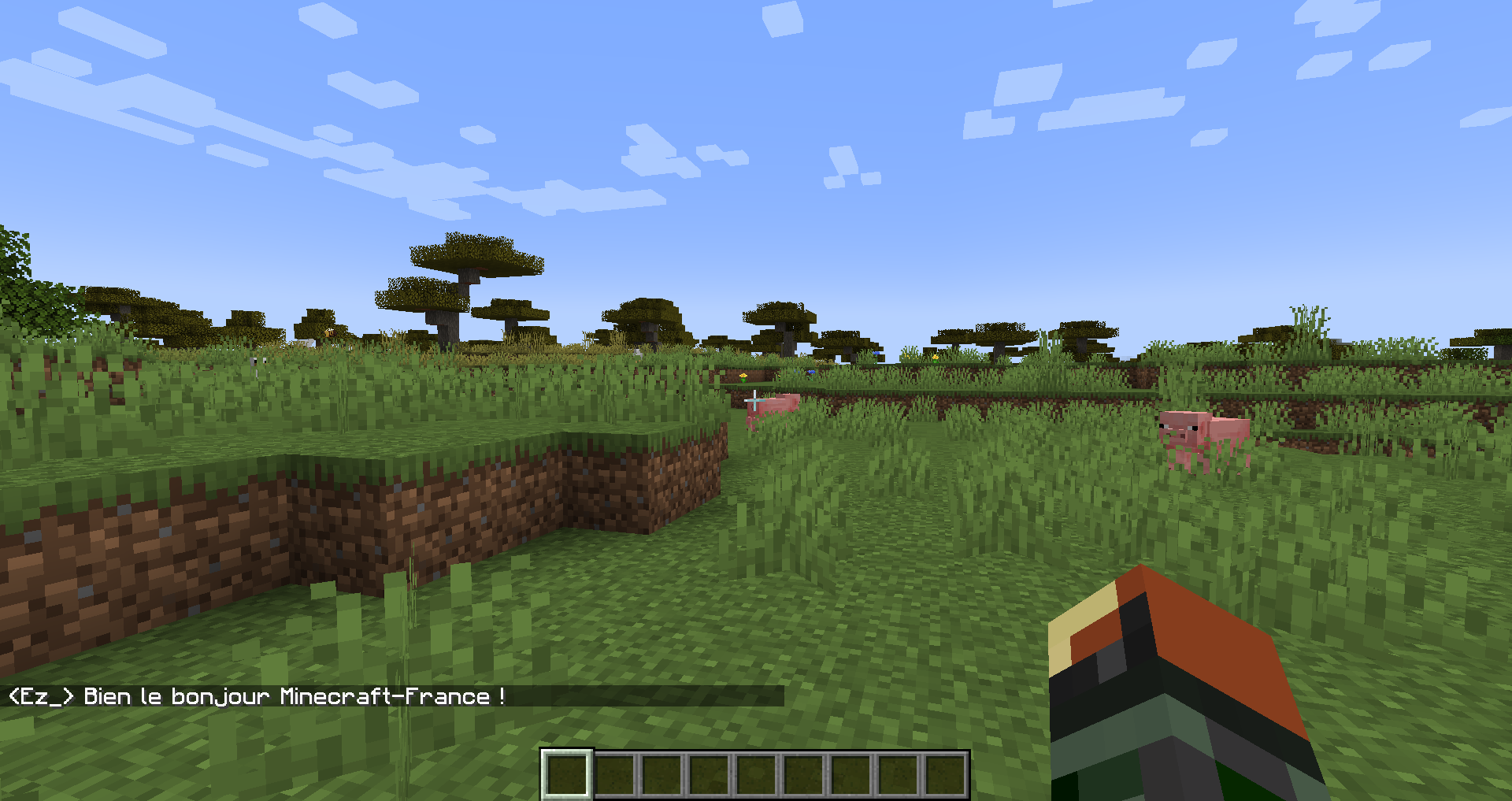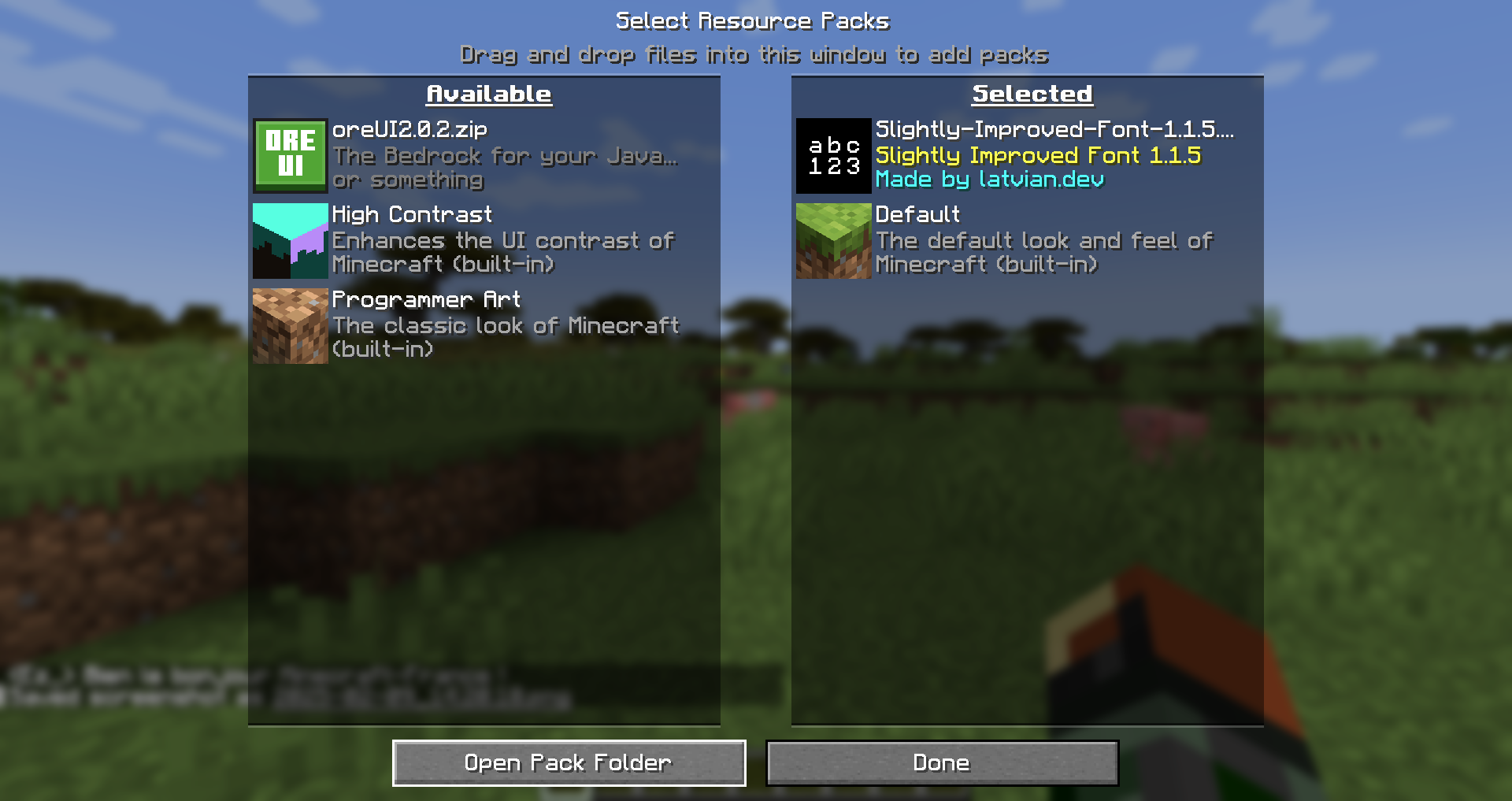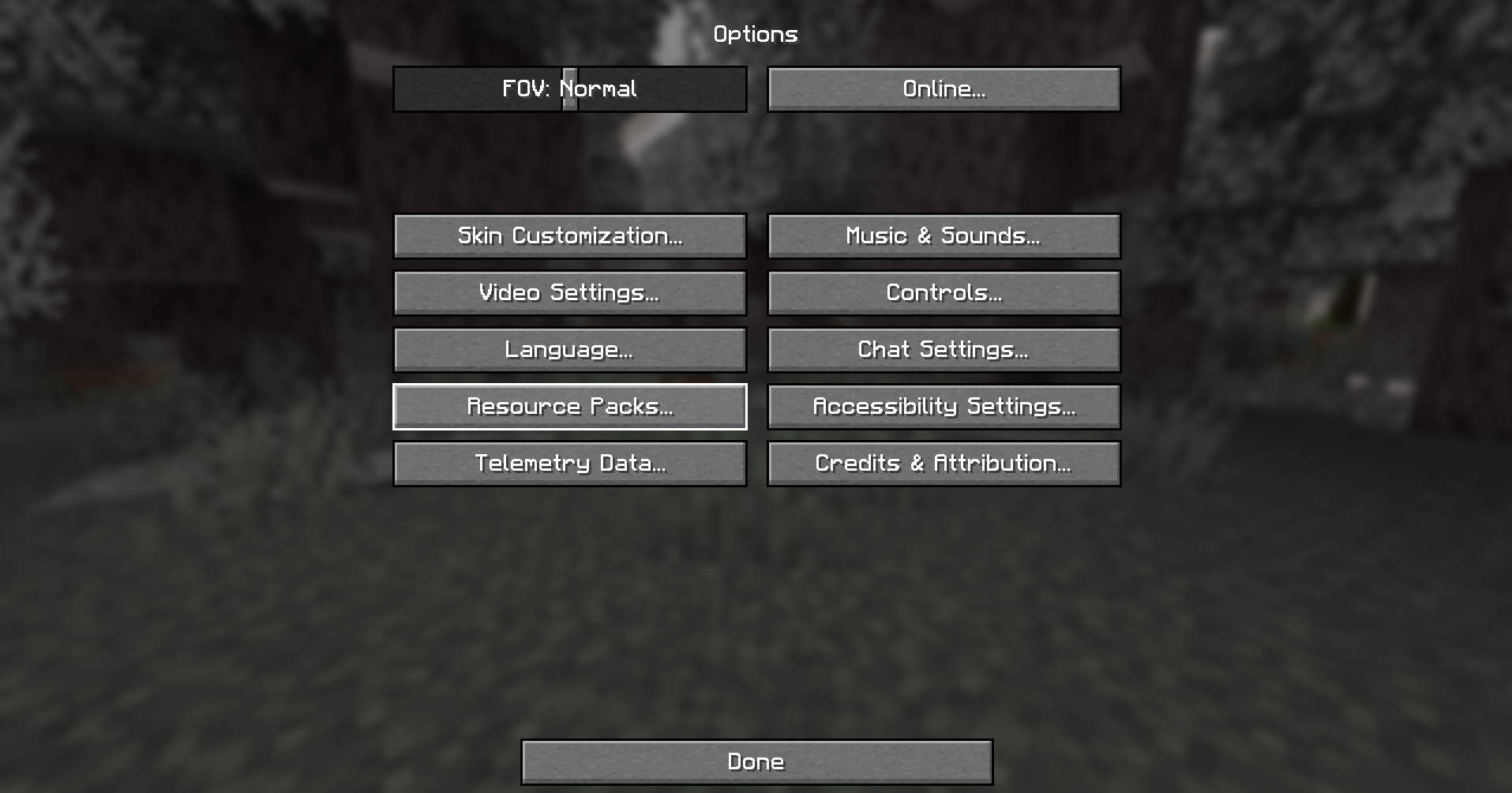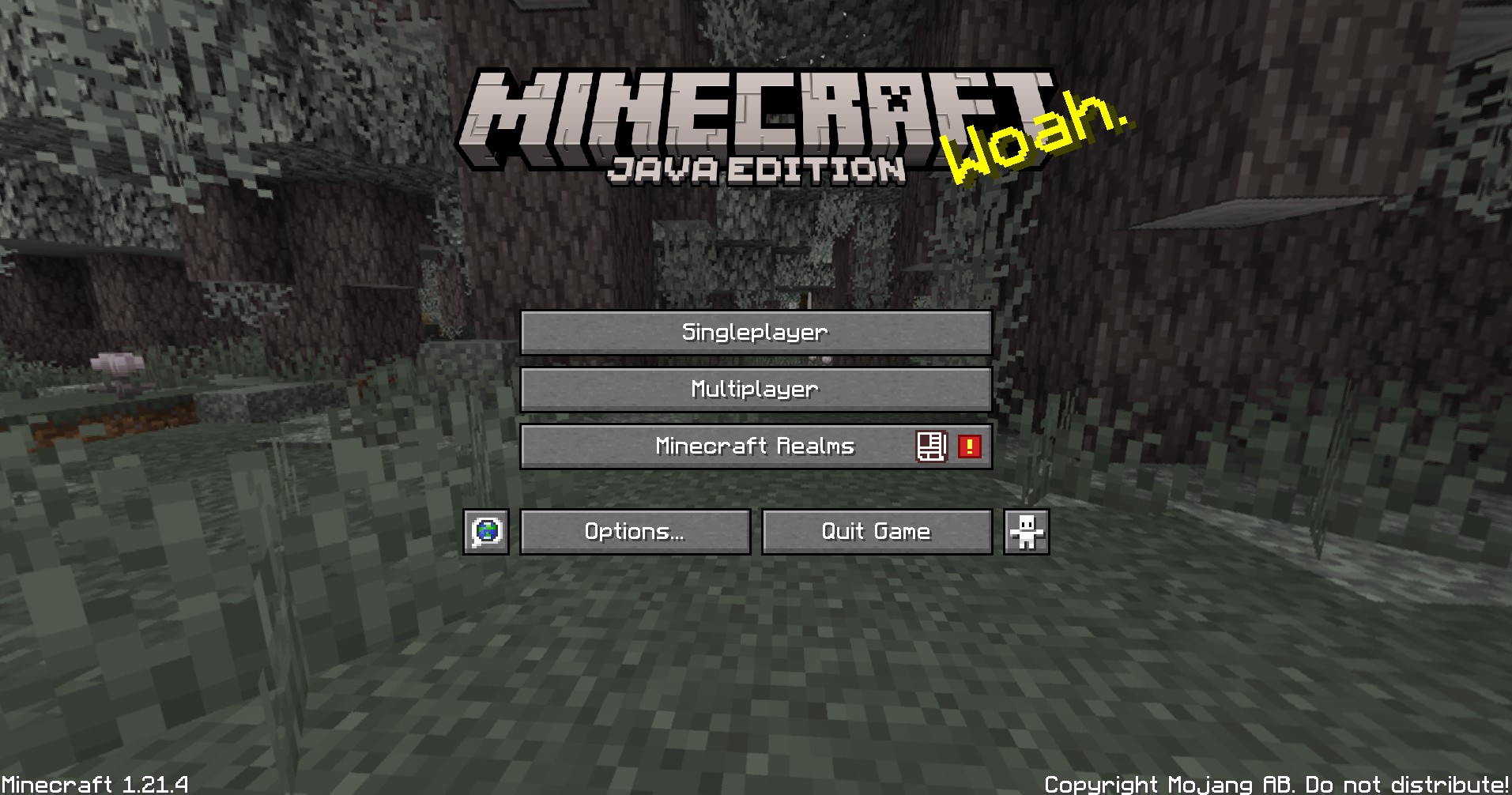
Slightly Improved Font est un pack de textures qui propose une amélioration subtile mais efficace de la police d’écriture de Minecraft. Son objectif est simple : redessiner la police d’origine du jeu avec une résolution de 32x, tout en conservant son style reconnaissable. Cette modification apporte une meilleure lisibilité sans dénaturer l’apparence classique du texte.
Une police optimisée pour un rendu plus net
Le pack Slightly Improved Font ne révolutionne pas l’apparence de Minecraft, mais il apporte un confort visuel amélioré grâce à un redessin minutieux des caractères. Il conserve les proportions et l’esthétique de la police d’origine, tout en offrant un rendu plus propre et plus fluide. Cette mise à jour s’applique à tous les caractères ASCII standards et aux symboles, garantissant ainsi une prise en charge complète des éléments textuels du jeu.
Slightly Improved Font